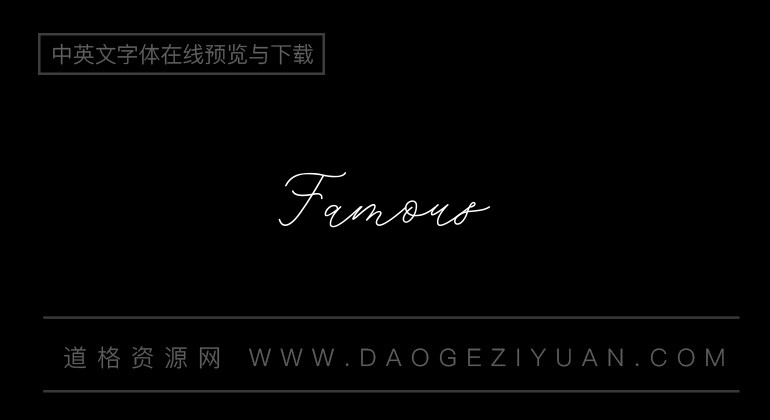
Famous
? Famous字体是一款拥有极简风格的字体,它有着流畅的线条和细节,为您的设计提供优雅的外观。Famous字体适用于任何类型的项目,包括海报、品牌标识、印刷品、网页和更多。它还可以用于品牌标识、标题、报纸广告、书籍封面等。Famous字体具有简洁、清晰、精致的外观,可以让您的设计在众多竞争中脱颖而出。
Famous是一款非常不错的手写艺术字体,具有很好的视觉感,适合于文化类的宣传设计、商业类品牌的广告和产品包装设计以及个性化文字排版等较多场景。